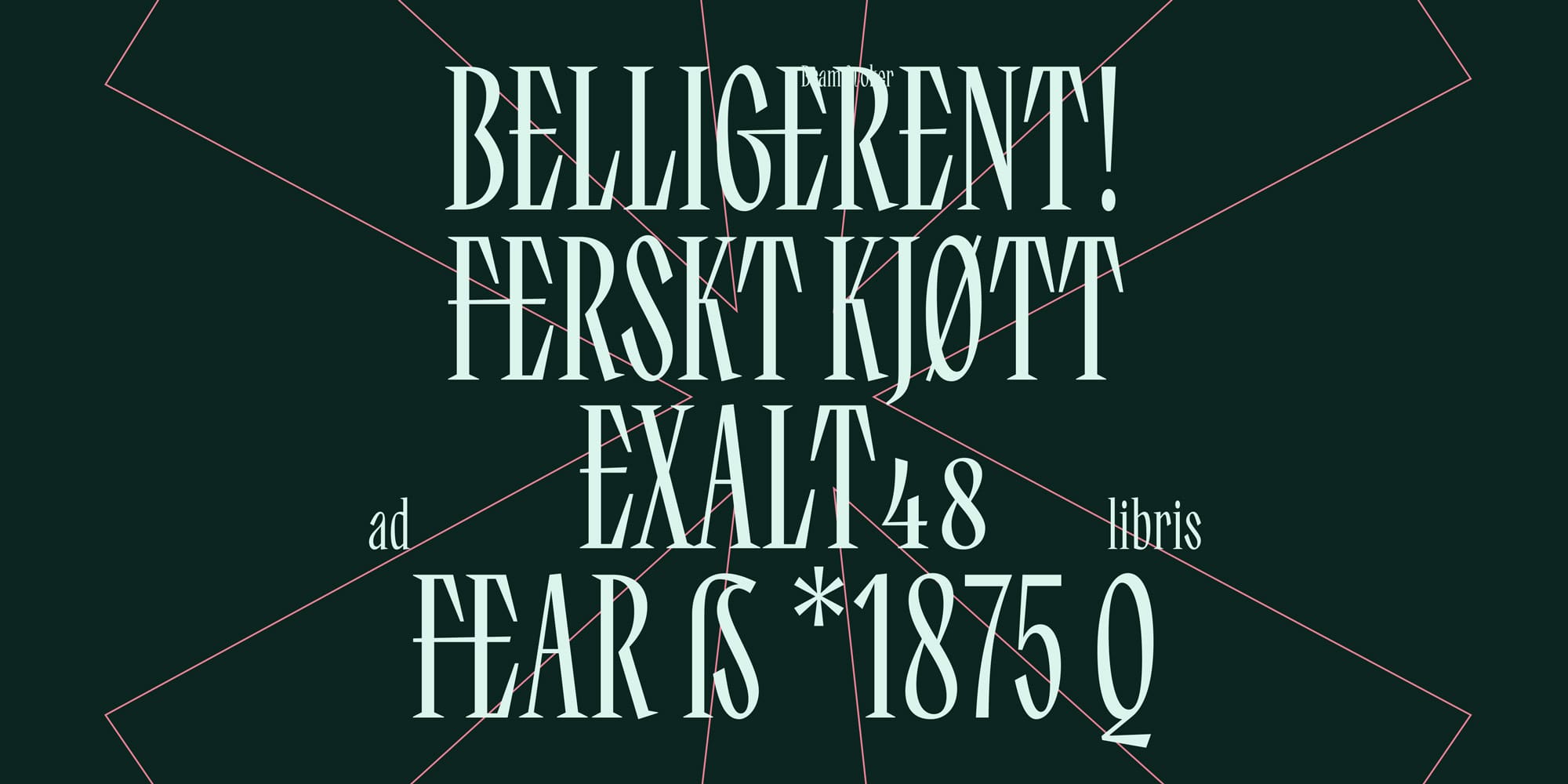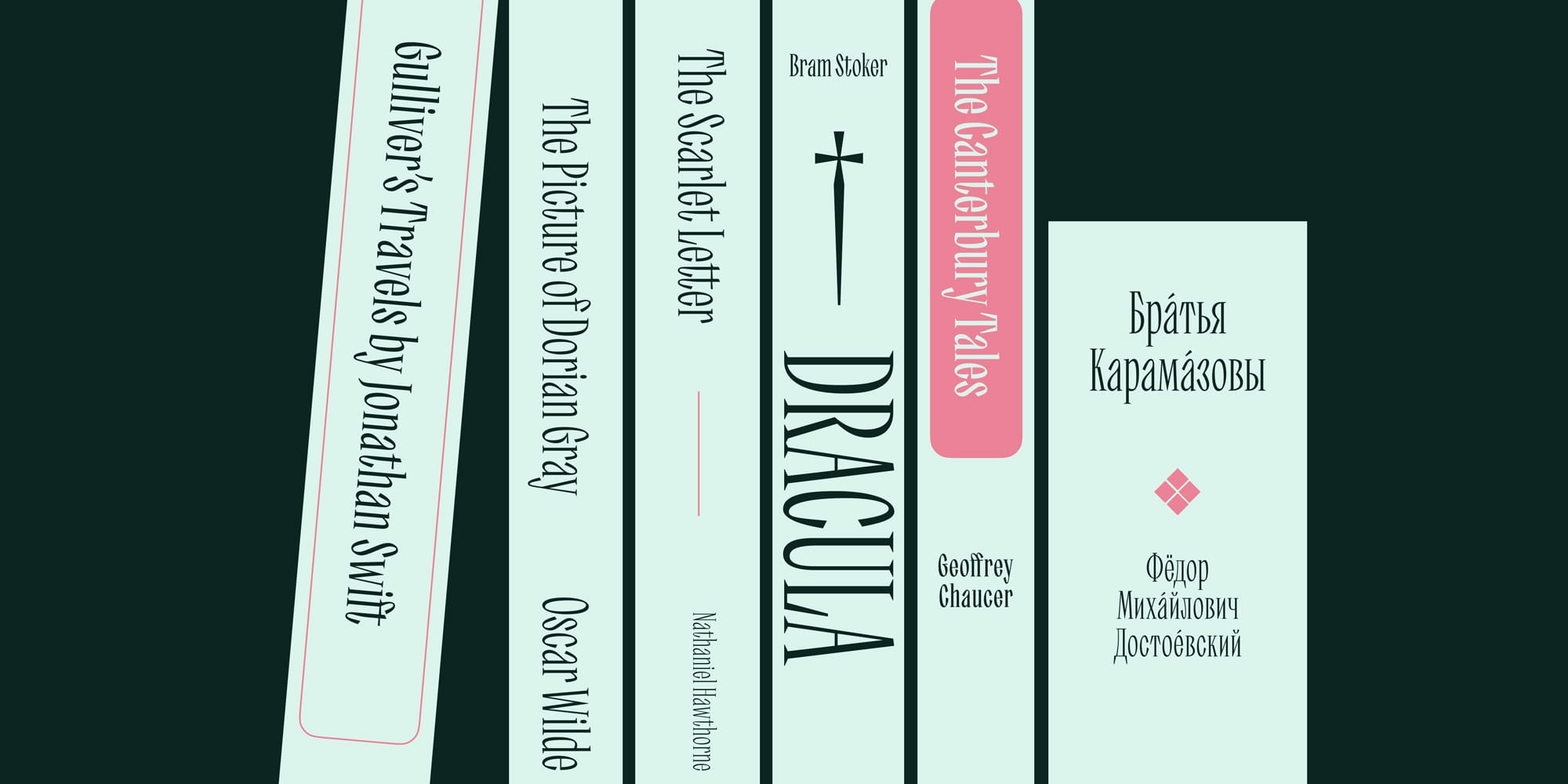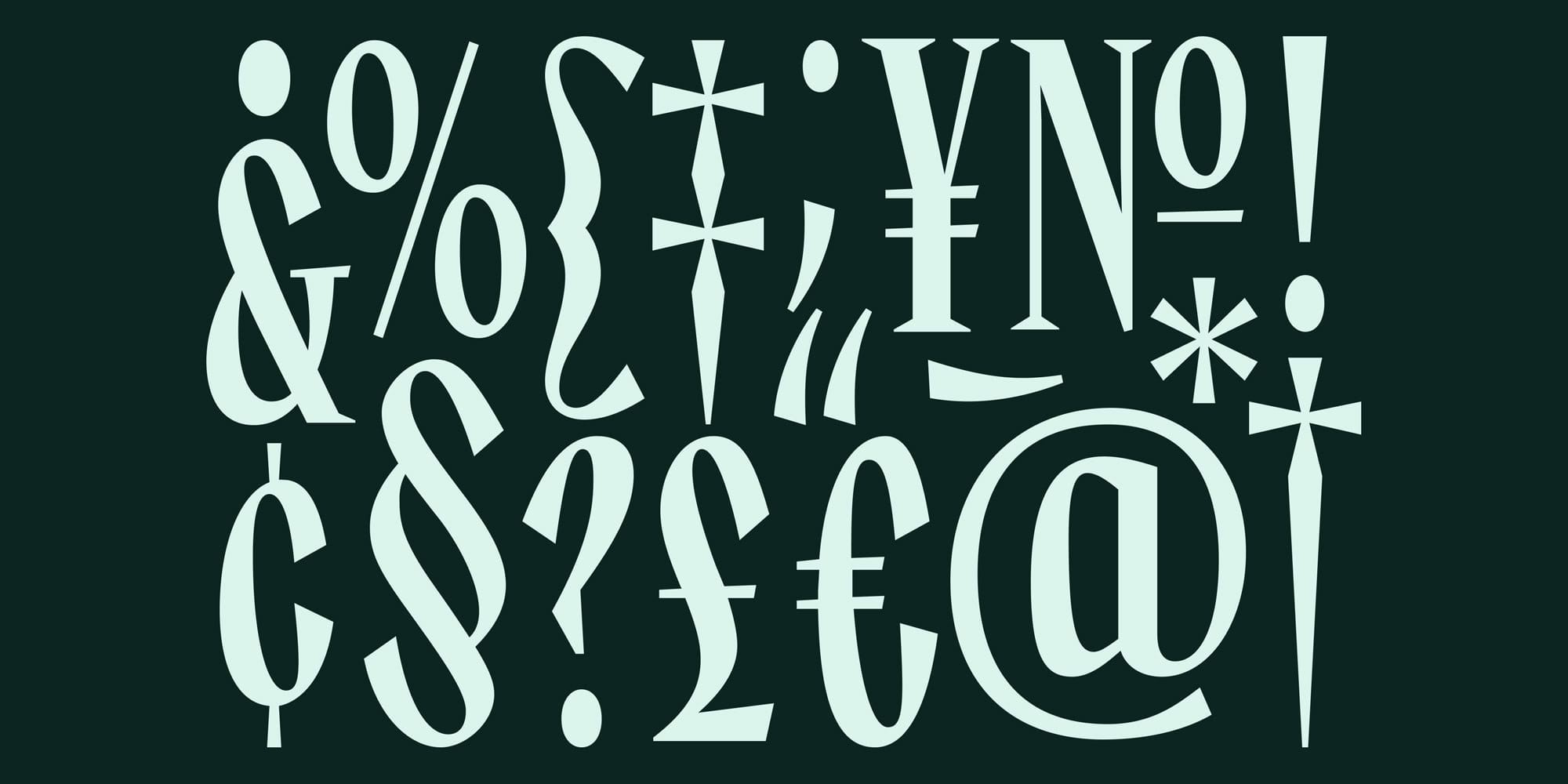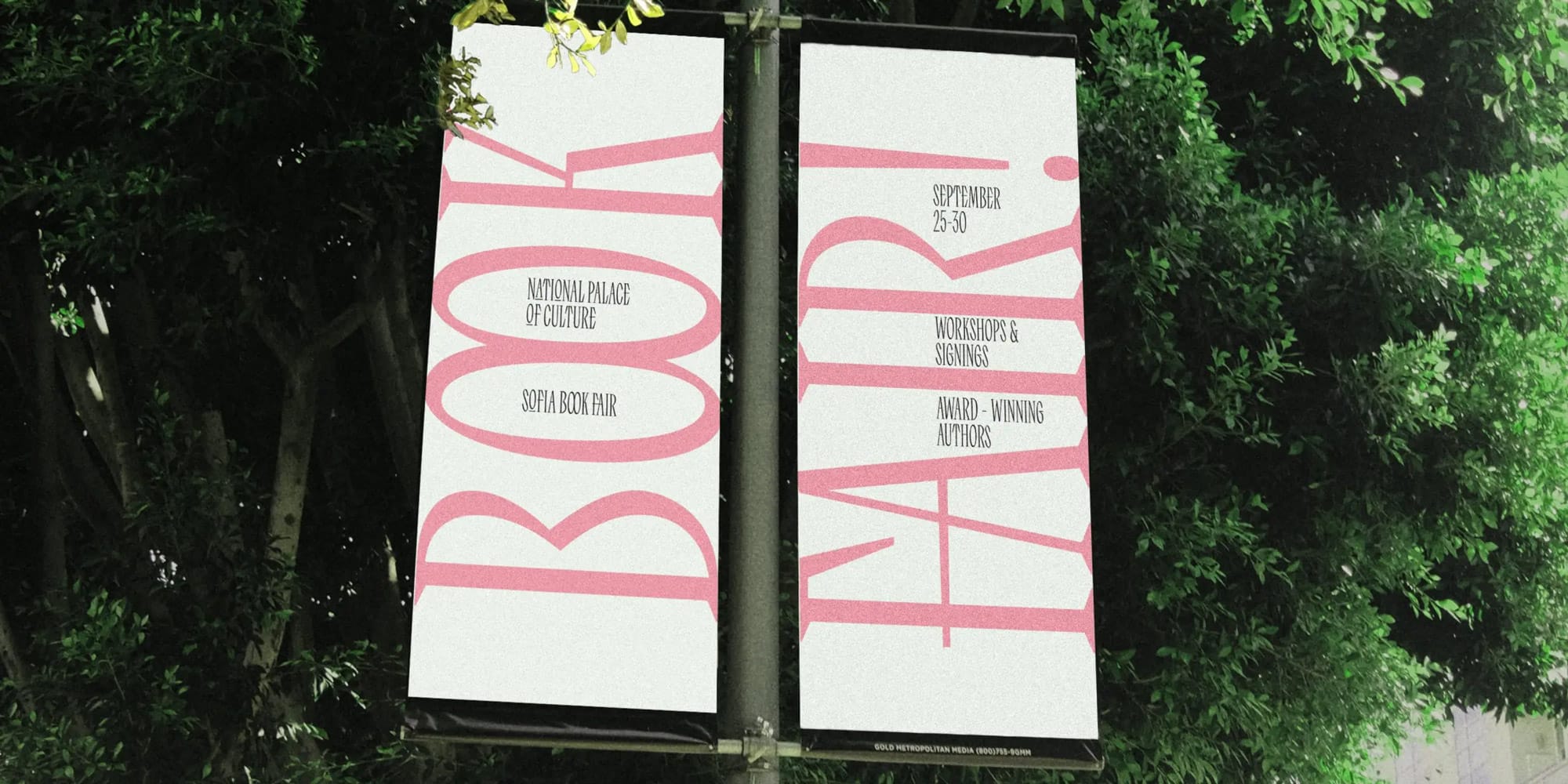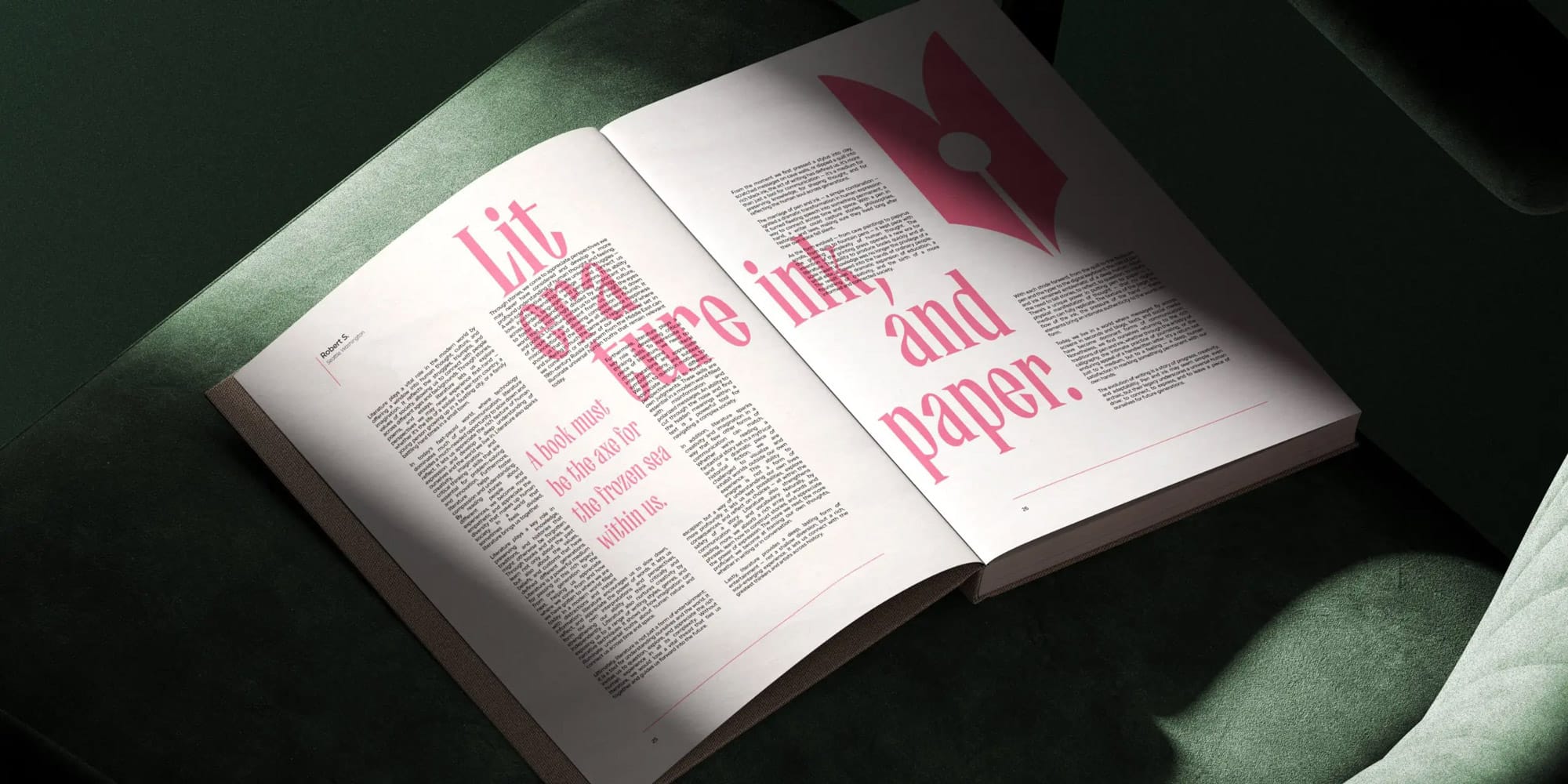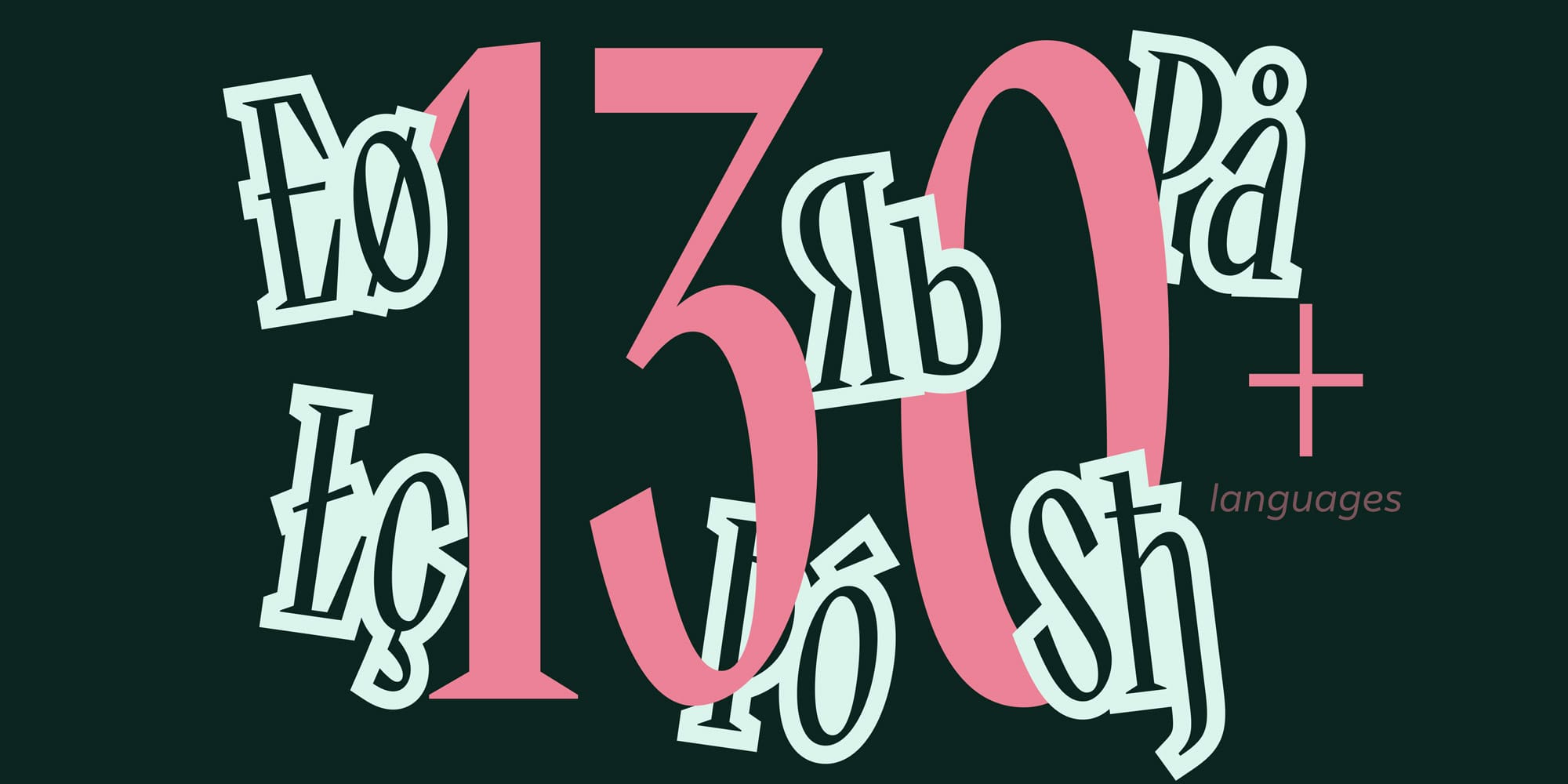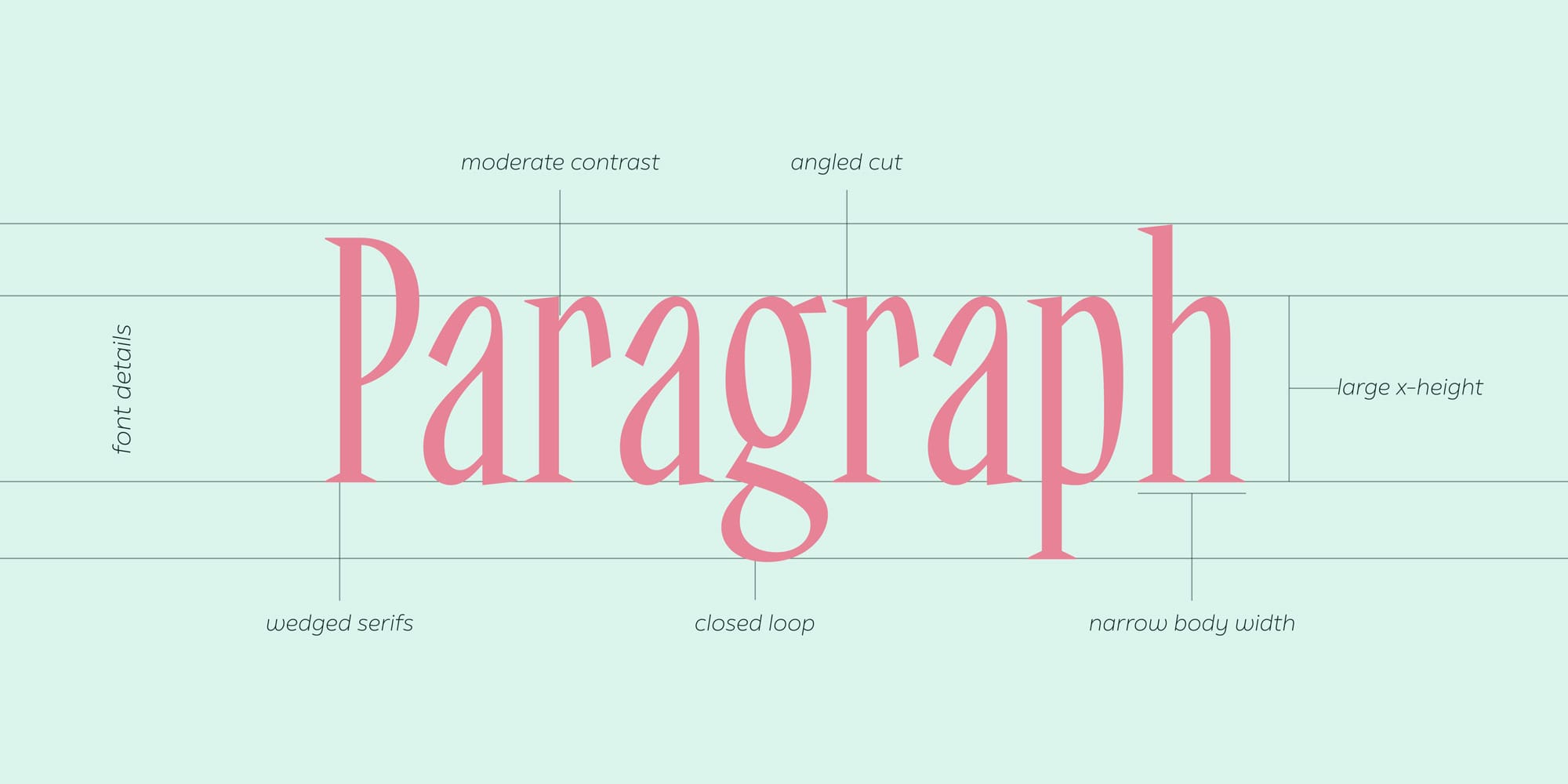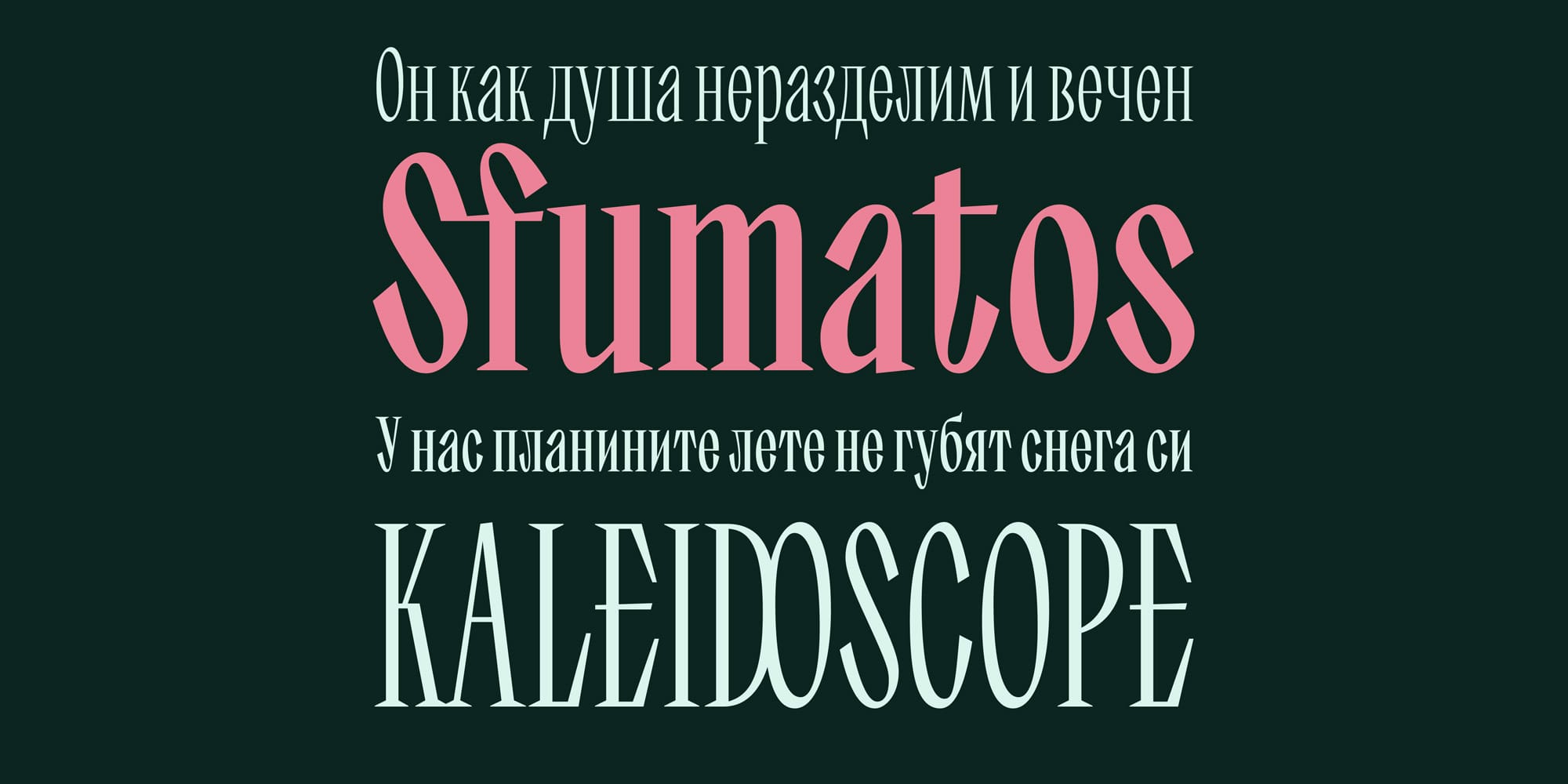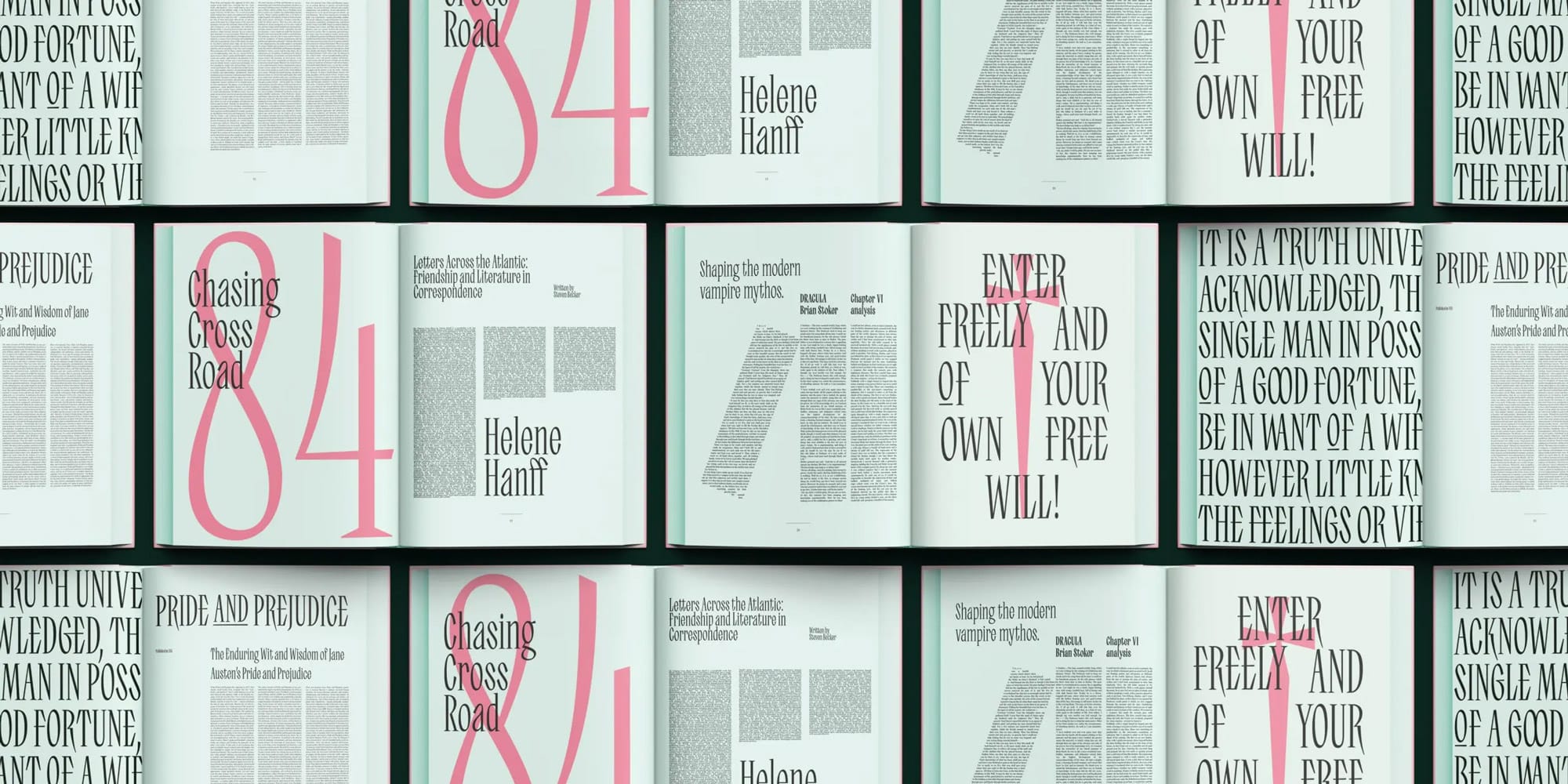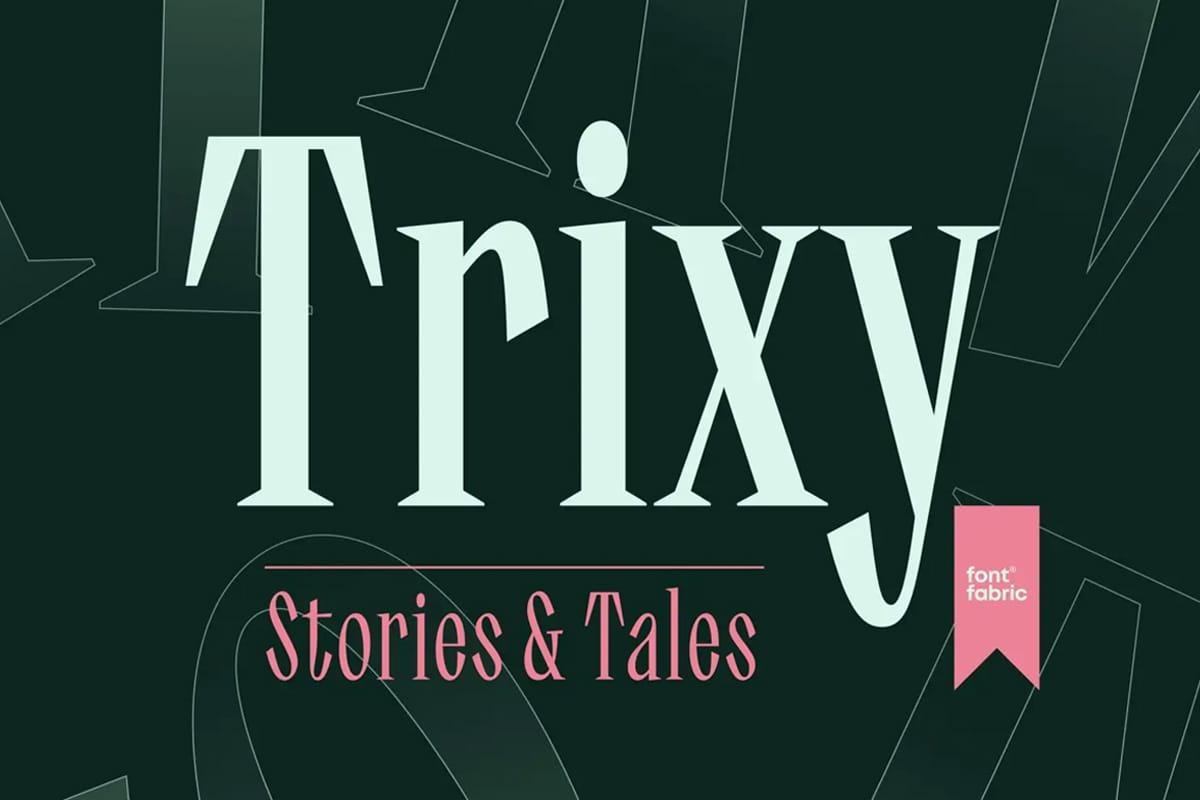
Trixy Font Family – bộ font serif condensed mới nhất từ Fontfabric lấy cảm hứng từ những bìa sách Liên Xô thời kỳ giữa thế kỷ 20 với chữ Cyrillic táo bạo, Trixy mang đến sự hẹp gọn, serifs sắc bén và độ tương phản cao, giúp các dự án của bạn nổi bật ngay từ cái nhìn đầu tiên.
Phát hành vào ngày 30/10/2025, Trixy font family nhanh chóng trở thành lựa chọn yêu thích của các nhà thiết kế branding, editorial và digital. Với 10 styles đa dạng, từ Light đến Bold + Variable, bộ font này không chỉ hỗ trợ Latin và Cyrillic mà còn tích hợp đầy đủ OpenType features. Nếu bạn đang tìm kiếm font serif condensed cho poster, bìa sách hay website, Trixy chính là “người bạn đồng hành” lý tưởng.
Đặc điểm nổi bật của bộ font Trixy
Trixy Font Family không chỉ là một bộ phông chữ — đó là cách bạn kể câu chuyện bằng hình dáng con chữ. Mỗi nét gạch, mỗi đường cong của Trixy đều mang hơi thở của sự tinh tế, táo bạo và đầy cá tính. Dưới đây là những yếu tố tạo nên sức hấp dẫn khó cưỡng của bộ font này:
Thiết kế Condensed Serif độc bản
Trixy sở hữu tỷ lệ chữ hẹp cùng các serif sắc như dao cắt, kết hợp với chi tiết có phần “lập dị” nhưng cực kỳ cuốn hút. Tất cả tạo nên một tổng thể retro đậm chất hoài niệm, song vẫn giữ được tinh thần hiện đại nhờ độ tương phản mạnh mẽ giữa các nét. Khi lên tiêu đề hoặc headline, Trixy mang lại cảm giác “sống động” và ấn tượng ngay từ ánh nhìn đầu tiên.
Hai subfamily linh hoạt – kể hai câu chuyện khác nhau
Trixy Stories: Gồm 5 trọng lượng (Light → Bold), mang phong cách thanh lịch, tinh tế với hệ ligatures và stylistic alternates phong phú. Đây là lựa chọn hoàn hảo cho những thiết kế cần chiều sâu cảm xúc, mềm mại và có tính biểu cảm cao.
Trixy Tales: Cũng gồm 5 trọng lượng, nhưng mạnh mẽ hơn với các chi tiết sắc nét và phần legs kéo dài kiểu swash. Nó toát lên năng lượng táo bạo, cực kỳ phù hợp cho logo, tiêu đề thương hiệu hoặc dự án sáng tạo đậm dấu ấn cá nhân.
Variable Fonts – công nghệ hiện đại cho trải nghiệm linh hoạt
Phiên bản Trixy Stories Variable và Trixy Tales Variable cho phép bạn điều chỉnh trơn tru giữa các trọng lượng, giúp giảm dung lượng file, tăng tốc độ tải web, đồng thời mang lại sự tự do sáng tạo tối đa trong từng dự án.
Hỗ trợ đa ngôn ngữ & OpenType hoàn chỉnh
Trixy hỗ trợ Latin mở rộng + Cyrillic đầy đủ, kèm theo hàng loạt tính năng chuyên nghiệp như alternates, ligatures, case-sensitive forms và stylistic sets. Dù bạn thiết kế trên Adobe Suite, Figma hay bất kỳ công cụ hiện đại nào, Trixy đều hoạt động mượt mà và ổn định.
Nhờ sự hòa quyện giữa công nghệ hiện đại, phong cách cổ điển và khả năng tùy biến vượt trội, Trixy Font Family trở thành lựa chọn hàng đầu cho các nhà thiết kế khi cần một font display serif vừa sang trọng, vừa có câu chuyện để kể — từ branding & packaging, editorial publishing đến advertising và digital design.